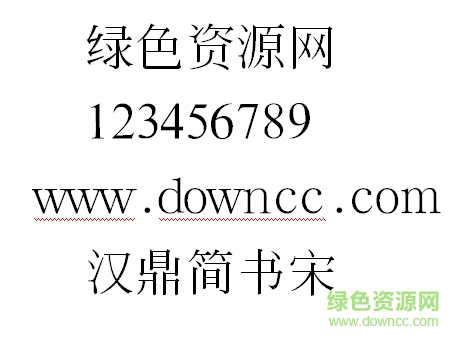
漢鼎簡書宋是一款比較常用的漢鼎字體。該字體的宋體特點不是很明顯,更具自己的特點,字形偏方正。喜歡的朋友,趕快下載體驗吧!
宋體,是為適應(yīng)印刷術(shù)而出現(xiàn)的一種漢字字體。筆畫有粗細變化,而且一般是橫細豎粗,末端有裝飾部分(即「字腳」或「襯線」),點、撇、捺、鉤等筆畫有尖端,屬于襯線字體(serif),常用于書籍、雜志、報紙印刷的正文排版。
宋朝文化興盛,印刷業(yè)有了巨大發(fā)展,從南宋時期,在臨安等地的印刷作坊里就開始出現(xiàn)了類似印刷體的字體,后世稱之為仿宋體。明朝時期,文人追捧宋刻本書籍,于是刻匠們加粗仿宋體的豎線和筆畫的端點以抵抗刻版磨損,卻依舊稱之“宋體”?,F(xiàn)代的所謂宋體基本上就是這樣成型的。